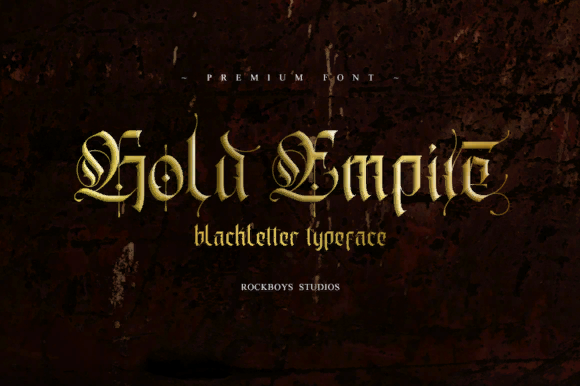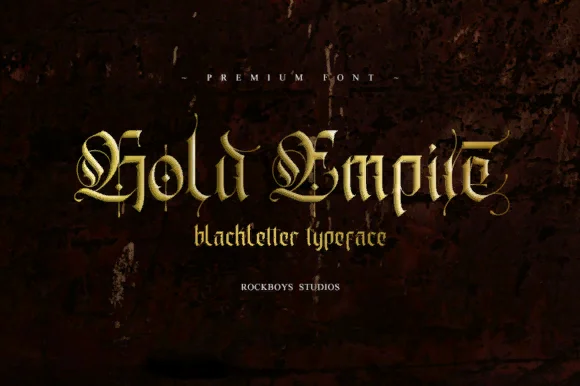
Название: Gold Empire Font (2021)
Gold Empire - это очень детализированный и элегантный шрифт с черными буквами.
Смело добавляйте его в свои любимые творения и позвольте себе поразиться полученному результату.